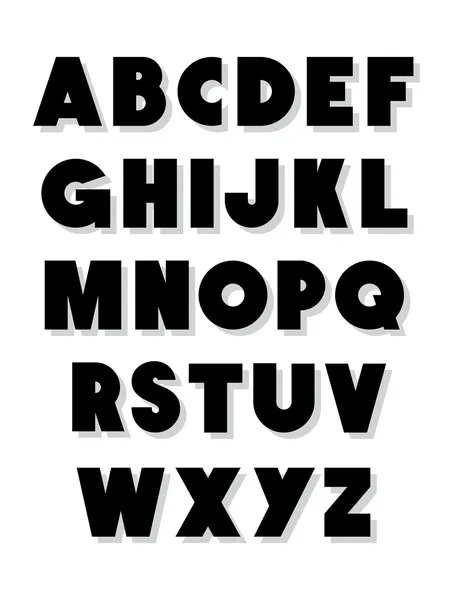
Шрифтовые ценности
Четыре взгляда на изменения в мире типографики
Двадцать шесть букв — это все, что английский язык дает человеку для описания всего, что мы видим, слышим, пробуем, вдыхаем, трогаем и воображаем. Есть только двадцать шесть букв и больше ничего, чтобы описать все, что мы делаем. Как же алфавит справляется с такой чудовищной нагрузкой?
За последнее десятилетие произошли огромные изменения не только в том, что мы говорим, но и в том, как мы выражаем свои мысли. По мере того, как перед типографикой возникают новые задачи, появляются новые носители информации и тексты с новым содержанием, требования к рисунку букв становятся день ото дня все сложнее. Форма букв, составляющих слово, так же как и его значение, стала играть важную роль в определении смысла послания (а также того, предназначено ли оно для нас или нет). Типографика как никогда раньше стала близка каждому из нас. Следовательно, изменения в этой области могут происходить не только по технологическим или культурным причинам, но и по личным или политическим.
Чтобы лучше понять те силы, которые стоят за изменениями в типографике, мы выбрали работы четырех дизайнеров, которые, по нашему мнению, лучше других демонстрируют изменения, произошедшие в мире шрифта. На примере Чанка Дизела мы рассмотрим состояние модной молодежной типографики. Вместе с Зузаной Личко из студии Emigre попробуем разобраться в тех задачах, которые ставят перед шрифтовым дизайном изменения в политике и экономике. А вместе с Джошем Бергером и Питом Маккракеном поговорим о культурных запросах новых медиа. И, наконец, с Мэтью Картером обсудим изменения в технологии.
Чанк: шрифты, которые создают человека
«В наше время шрифты становятся все более тенденциозными», — считает Чанк Дизел, дизайнер шрифтов из Миннеаполиса, автор Fornificator, Mr. Frisky и Chauncy Fatty. «Здорово быть посреди всего этого, потому что через пару лет все, что мы делаем сейчас, будет выглядеть довольно глупо». Настоящее имя Чанка -Чарльз Андерсон (Чанк не хотел, чтобы его путали с известным графиком-дизайнером Чарльзом М.
Выполненные в стилистике пост-панка шрифты Чанка можно встретить где угодно: от стен Национального музея дизайна Купер-Хьюитт в Нью-Йорке до банки с содовой водой в вашем магазинчике на углу. «Грейп-сода — любимый напиток насекомых, обитающих на помойках. Я — часть городского распада», — рассказывает дизайнер.
История Чанка — это во многом и история целого направления в типографике — «гранж» (в изменчивом мире шрифтового дизайна это словечко уже перестало считаться модным). Татуированные и украшенные пирсингом (от английского pierce — прокалывать — увлечение прокалыванием металлическими украшениями различных, подчас весьма неожиданных частей тела, — прим. ред.) шрифты «гранж» вышли на сцену вместе со странными личностями из киберпространства. Появившись сперва в журналах и на обложках альбомов, со временем они растворились в тумане (буквально «разблюрились») в фирменных портфолио и пригородных супермаркетах.
Но по дороге случилось нечто совершенно невероятное — молодежь решила, что шрифты — это круто. В пантеоне нового поколения шрифт занял почетное место вслед за «гаражными» группами, роликовыми досками и видеоиграми. Сайты, предлагающие бесплатные шрифты, растут как грибы после дождя. Небольшие «экспериментальные» фирмы, такие, как T-26, Garage Fonts, House Industries котируются наравне с Monotype, Agfa и Adobe. И многие полагают, что монстры шрифтовой индустрии уже проигрывают. У шрифтовых дизайнеров из малых фирм появились поклонники и, что самое важное, — деньги.
Существует несколько объяснений происхождения и популярности новой типографики. Это может быть эффект постпостмодернизма, или попытка создать более эффективную рекламу в условиях дефицита внимания, или отражение расколотого общества.
Чанк более прозаичен. В журнале Cake, где он работал главным художником, «мы использовали самый быстрый и дешевый принтер, который только смогли найти.
Печать была очень грязной — все мелкие детали расплывались. Поэтому дизайн должен был быть действительно мощным в своей основе». Как каждый уважающий себя издатель модного журнала, нуждающийся в супер-шрифте, Чанк создал свою собственную гарнитуру.
«Огромную роль сыграло распространение Kinko (сеть салонов оперативной печати)», — добавляет Чанк. «Ребятам в этих конторах быстро надоела их работа и они начали развлекаться — печатали флайеры для своих групп, обложки к альбомам, неважно, что они понятия не имели о том, как это делается». Самиздат быстро становится популярным среди тинейджеров и возникает новый стиль: облупленные буквы, скверный дизайн и т. д.
Чанк считает, что есть и еще одна связь между шрифтами «гранж» и новым поколением. «Посмотрите на пацанов, которые бесплатно выкладывают свои шрифты на Geocites — большинство из них впервые включили компьютер, чтобы поиграть в видеоигры. В каком-то смысле, похоже, они все еще играют».
Как и у многих его современников, работы Чанка доступны, беззастенчивы и подвержены тлетворному влиянию поп-культуры.
Шрифты, кажется, живут своей собственной жизнью — жирные начертания у Чанка «пухлые» или «толстые», курсивная версия Parkway варьируется от «Мотеля» к «Отелю». Отличный пример того, как шрифты Чанка находят путь к своей аудитории на уровне, далеком от печатных страниц — серия Rock Star Fonts Archive (шрифты рок-звезд), основанная на почерках известных музыкантов. (Вы можете скачать полученную шрифтятину с элементами почерка М. Даути из Soul Coughing, Марка Сэндмана из Morphine и Николь Блэкман из Golden Palominos по адресу: www.tripod.com). По словам Чанка, когда он создает новый шрифт (а делает он это с ошеломляющей скоростью), его скачивают до 10 тыс. человек. Когда-то просто псевдоним веб-серфера, сегодня слово «Чанк» стало популярной торговой маркой.